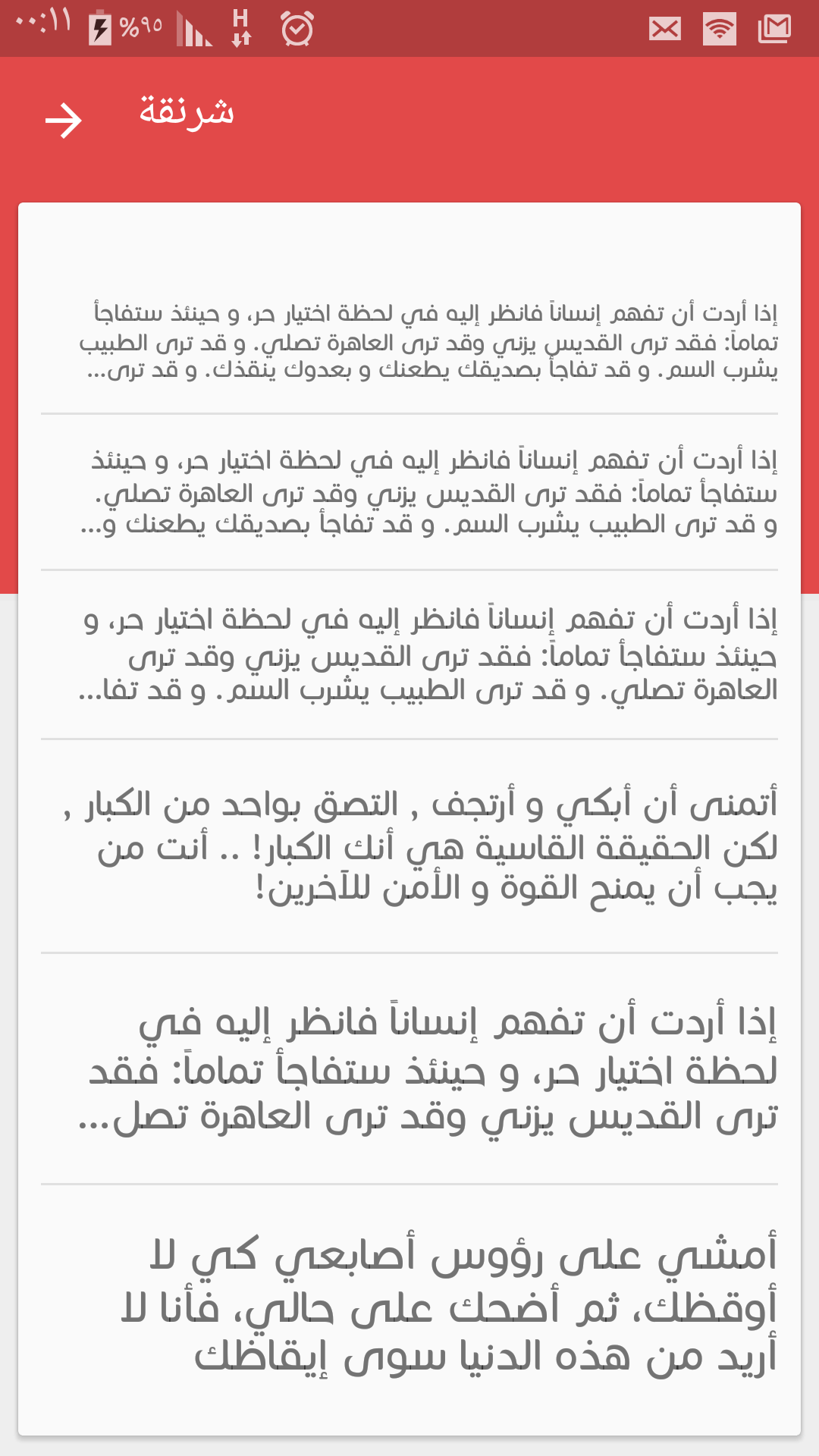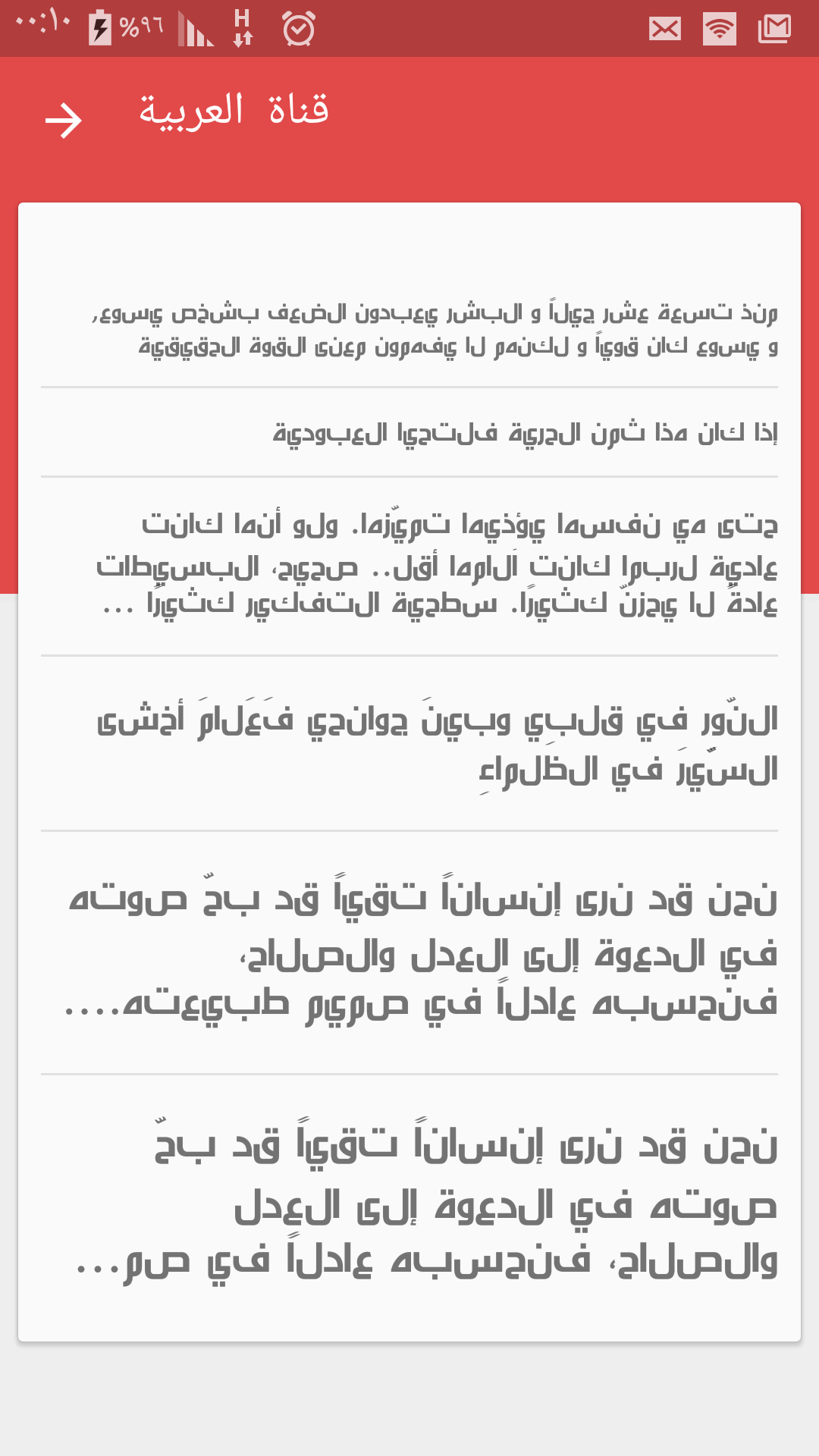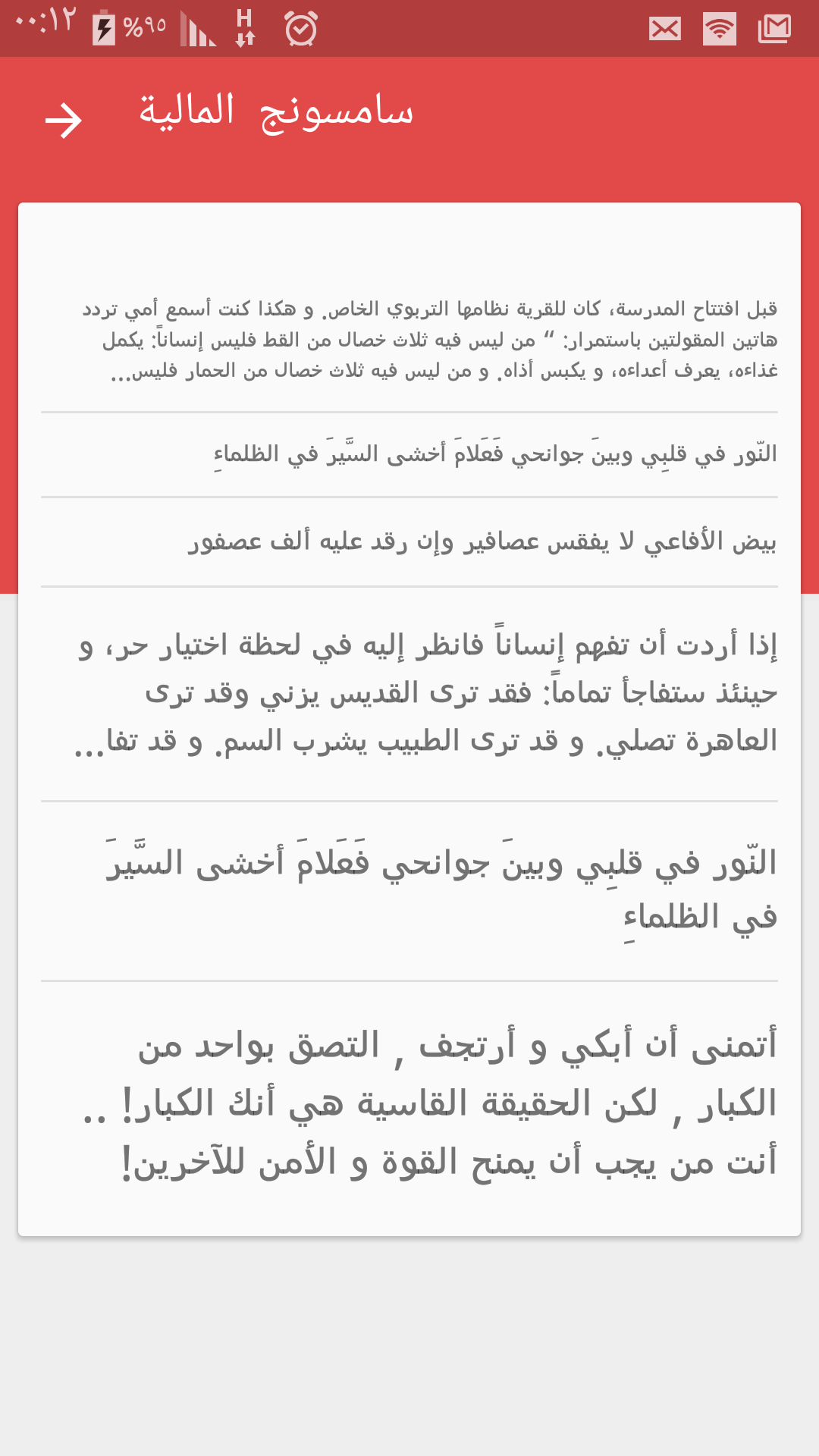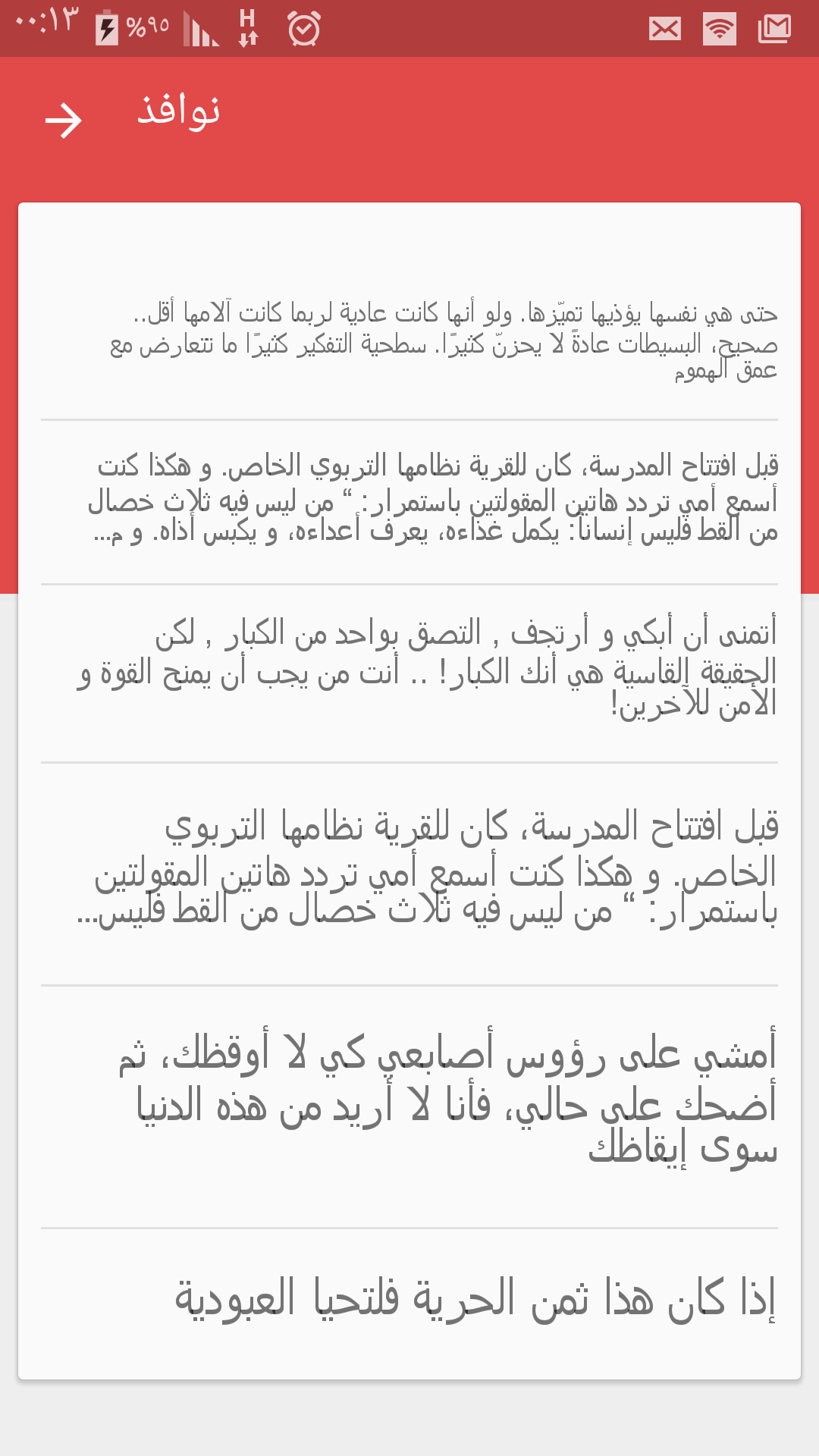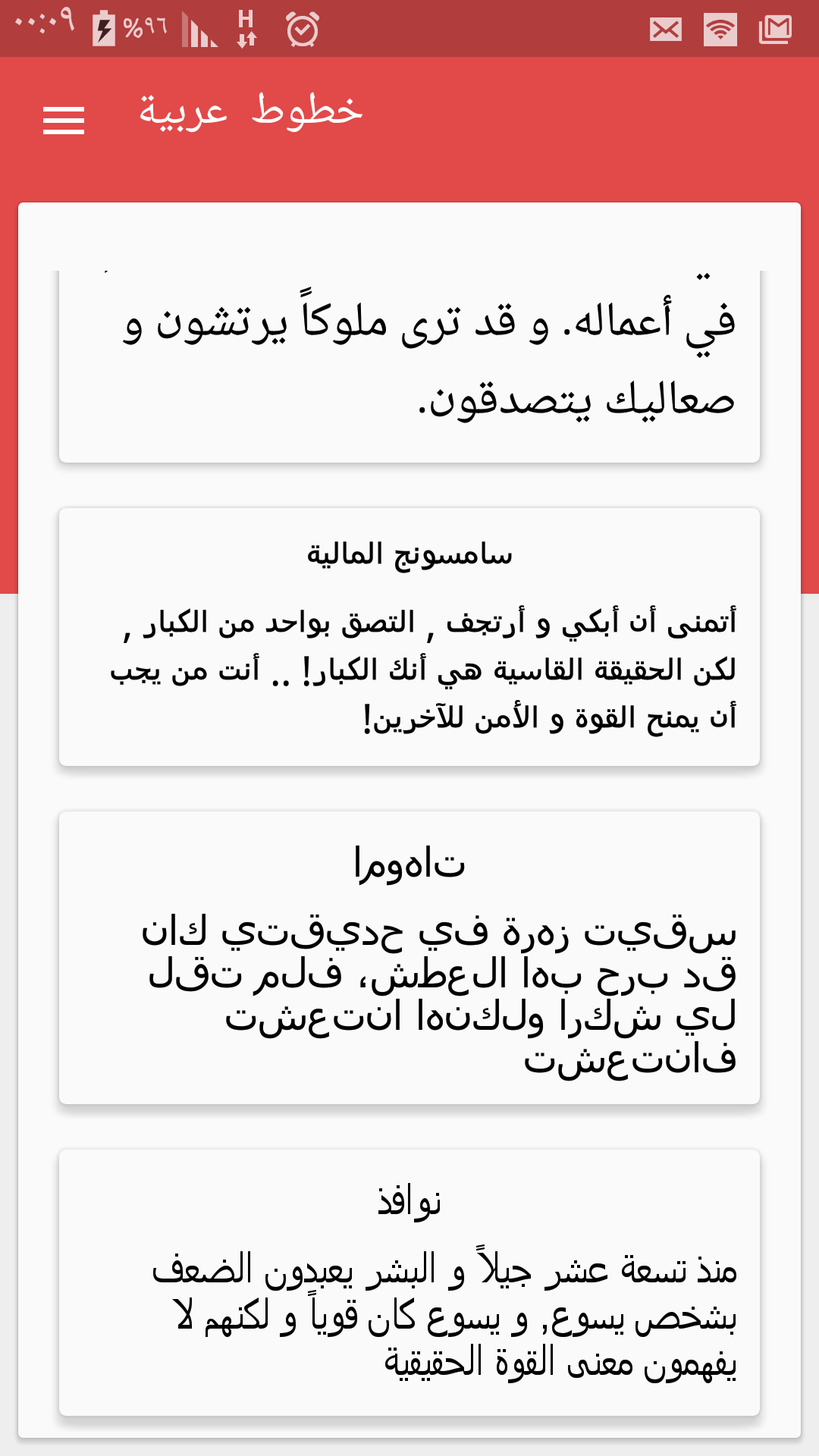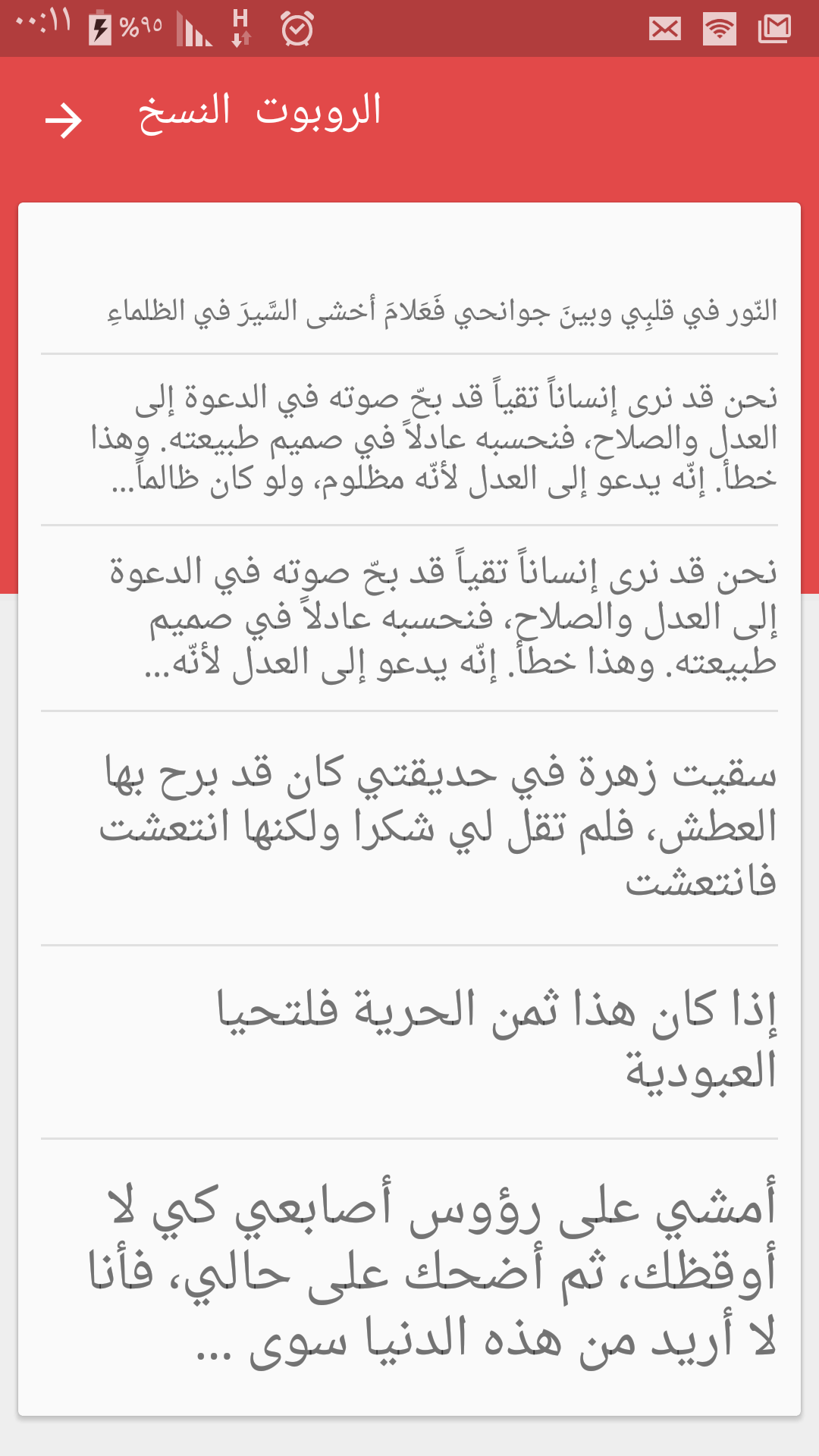
Cute Arabic Fonts for FlipFont فونتهای عربی زیبا برای FlipFont
Cute Arabic Fonts for FlipFont
فونتهای عربی زیبا برای FlipFont
این مجموعه فونت های خارق العاده ای برای Samsung Galaxy شما است. با طیف گسترده ای از قلم های دست نویس درون بسته بندی ، از ظاهر جدید لذت ببرید.